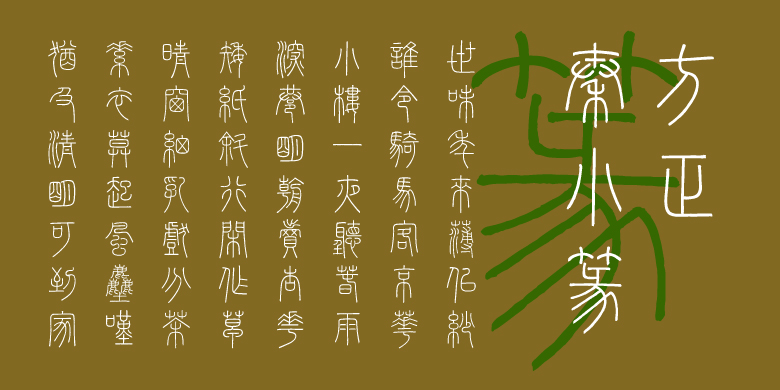
方正秦小篆
• 整理/设计:
贺进
常规书写·毛笔
关于秦小篆:
秦代小篆,又称秦篆,是秦始皇“书同文”政策下产生的官方标准字体,是中国历史上第一次由国家主导的、系统性的文字规范化成果,在汉字发展史上具有里程碑式的意义。
李斯是“书同文”的主要倡议者和执行者,也是当时最负盛名的小篆书法家。相传秦代的重要纪功刻石均由其手书,其中《峄山刻石》是他的代表作之一,虽然现存的是宋代摩刻本,但仍然是学习小篆的最佳范本之一。
字体特征:
方正秦小篆是以《峄山刻石》的字形特点为基础临创开发的,笔画匀称圆润,结构对称严谨,形体修长,线条如“玉箸”般温润流畅。
临创者:贺进
整理/设计:杨龙龙、史通通、韩文静、冯红晨、张培艳